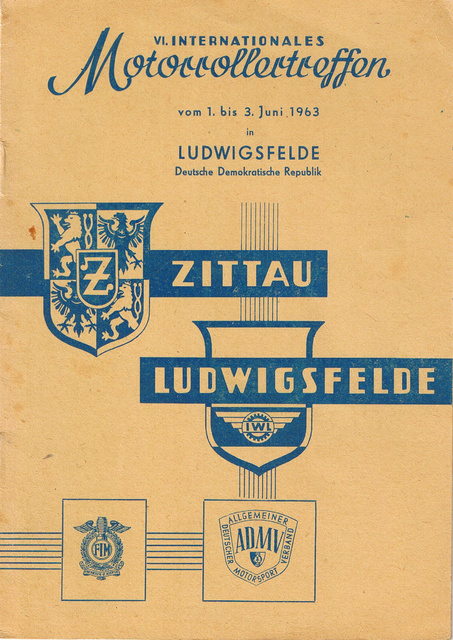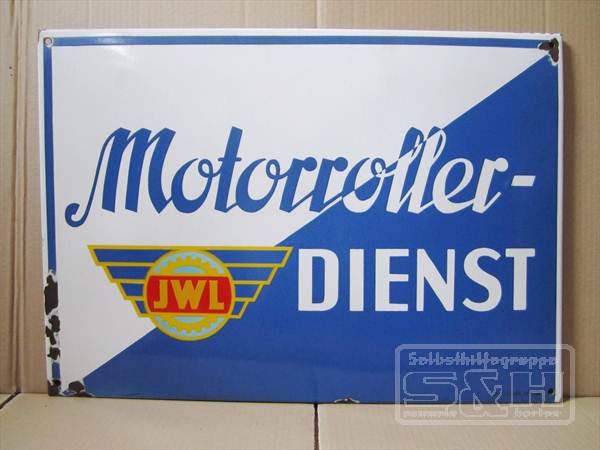
DDR Schrift der 50er-70er Jahre - Handwritten
vorweg möchte ich meine Hochachtung vor dem ausdrücken, was Sie hier machen. Die Kunst der Typografie ist auch für mich sehr spannend. Auch wenn Sie hier bestimmt viele "Eintagsfliegen" wie mich erleben, möchte ich Sie bitten mir weiterzuhelfen.
Wir sind eine kleine Interessensgemeinschaft von Oldtimerliebhabern und erstellen als Bindeglied zu unserem Hobby eine jährliche Ausgabe eines hochwertigen A3 Kalenders. In diesem Jahr habe ich zwei originale Bilder aus den 60er Jahren
nachzeichnen lassen und suche dazu eine zu der Zeit passende Schriftart. Die beiden Bilder können Sie sich auf meiner Seite unter www.iwl-kalender.de unter dem Punkt Kalender 2013 anschauen. Im Bezug auf unsere IWL Roller tauchte in den 60er Jahren immer wieder eine bestimmte Kombination aus verschiedenen Schriftarten auf. Mein Interesse fällt auf die handgeschriebene Schriftart "Motorrollertreffen", die ich in keiner Schriftbibliothek finden konnte. Auf dem ersten angehängten Bild können Sie sich einen Überblick über ein Plakat verschaffen, wo das Wort "Motorrollertreffen" in der gesuchten Schriftart auftaucht. Weitere Plakate hab ich ebenso in digitaler Form, wo diese Schriftart wieder vorkommt.
Können Sie mir weiterhelfen?
Eine ähnliche Schriftart konnte ich hier auf dem Emailleschild entdecken.
Ich glaube hier wurde schon öfter festgestellt, dass Fonts zu deutschen Plakathandschriften selten sind. Diese typisch amerikanischen Vintage-Lettering-Fonts gibt es wie Sand am Meer*.
Aber ein Tipp wären durchaus die Zierfische
* ... aber vielleicht ist da ja trotzdem was bei, oder hier: